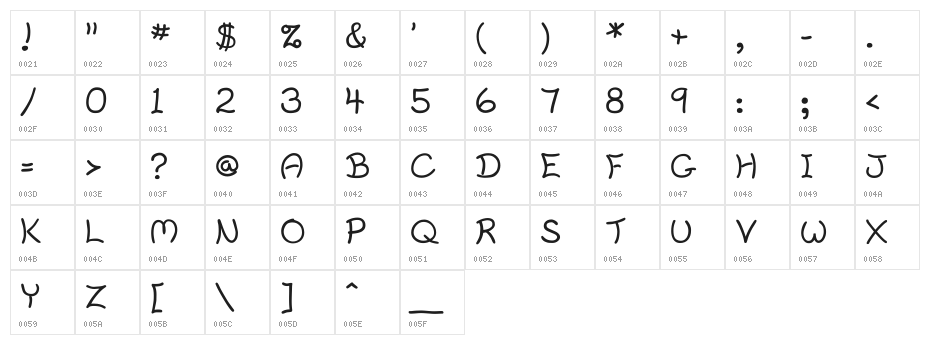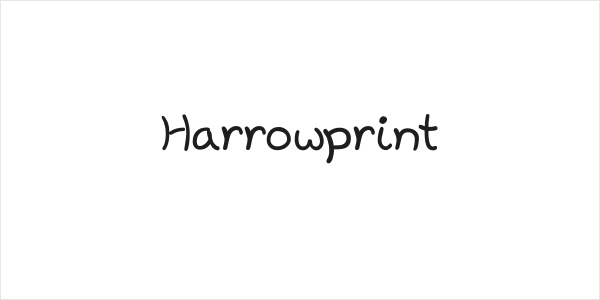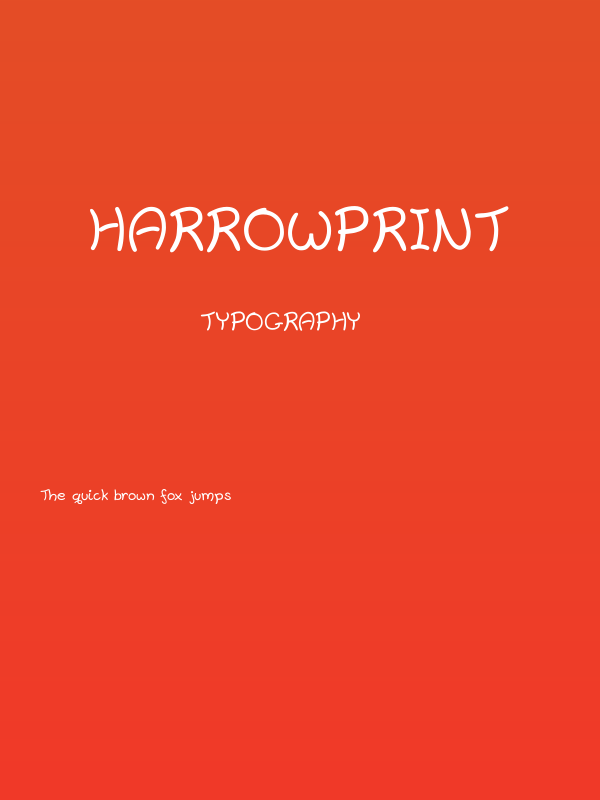
Harrowprint Font
| النمط العام | Playful |
| حالة الاستخدام | Headlines, Logos, Informal Text |
| مشاريع مقترحة | Ideal for children's books, greeting cards, playful branding, and casual invitations. |